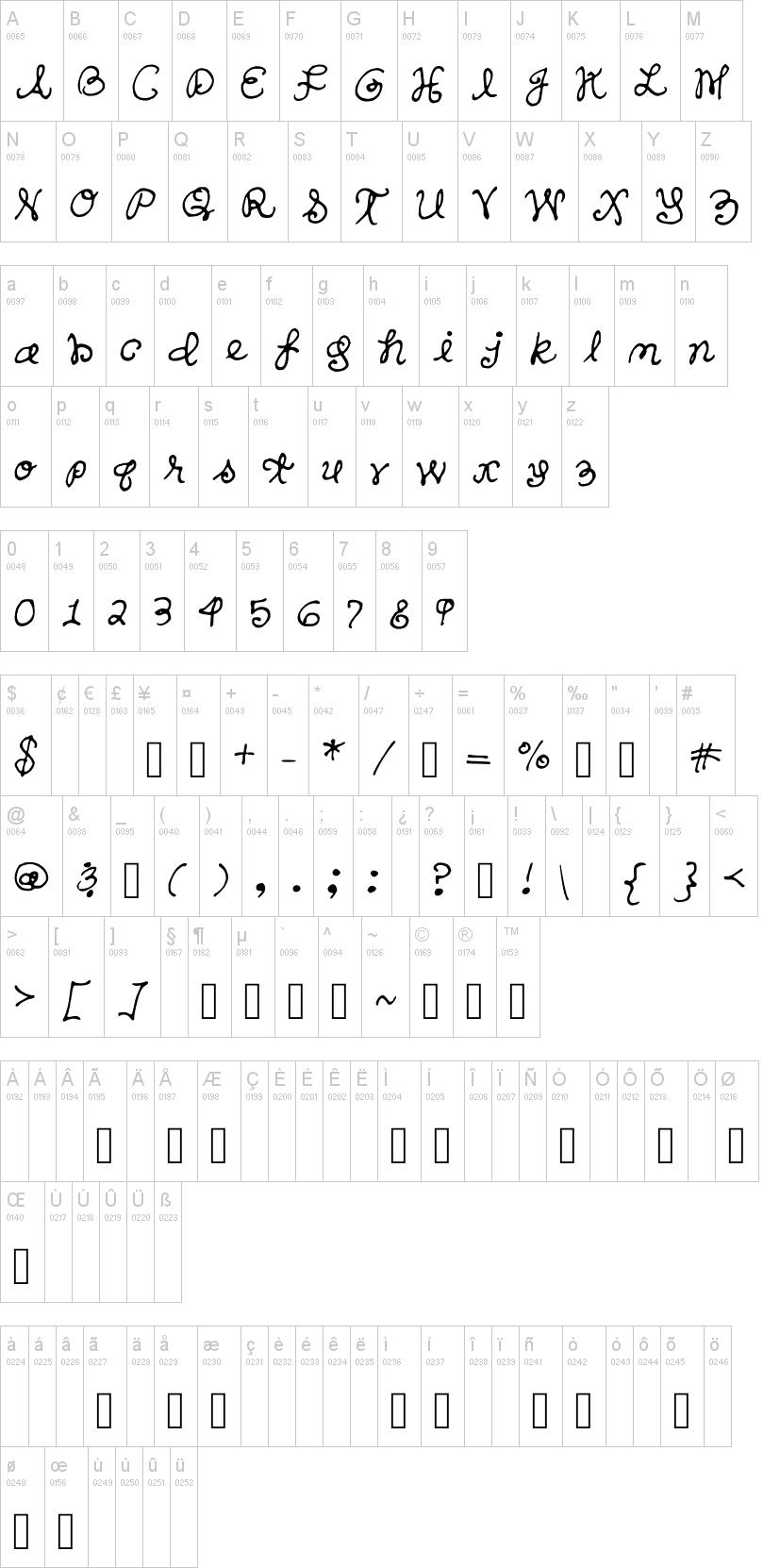
Sanders Hand是一款手写风格的英文字体,由英国设计师Ben Sanders设计,它拥有独特的手写风格,可以让你的文字显得更加自然,更有生命力。它的字体特点是每个字母都有一个温柔的曲线,使得文字看起来更加温暖,有趣,而且还有一种细腻的质感,使得文字充满了活力。Sanders Hand字体适合用于节日卡片,婚礼邀请函,日记,海报,品牌标识等等。内容介绍
Sanders Hand是一款非常不错的手写艺术字体,具有很好的视觉感,适合于文化类的宣传设计、商业类品牌的广告和产品包装设计以及个性化文字排版等较多场景。